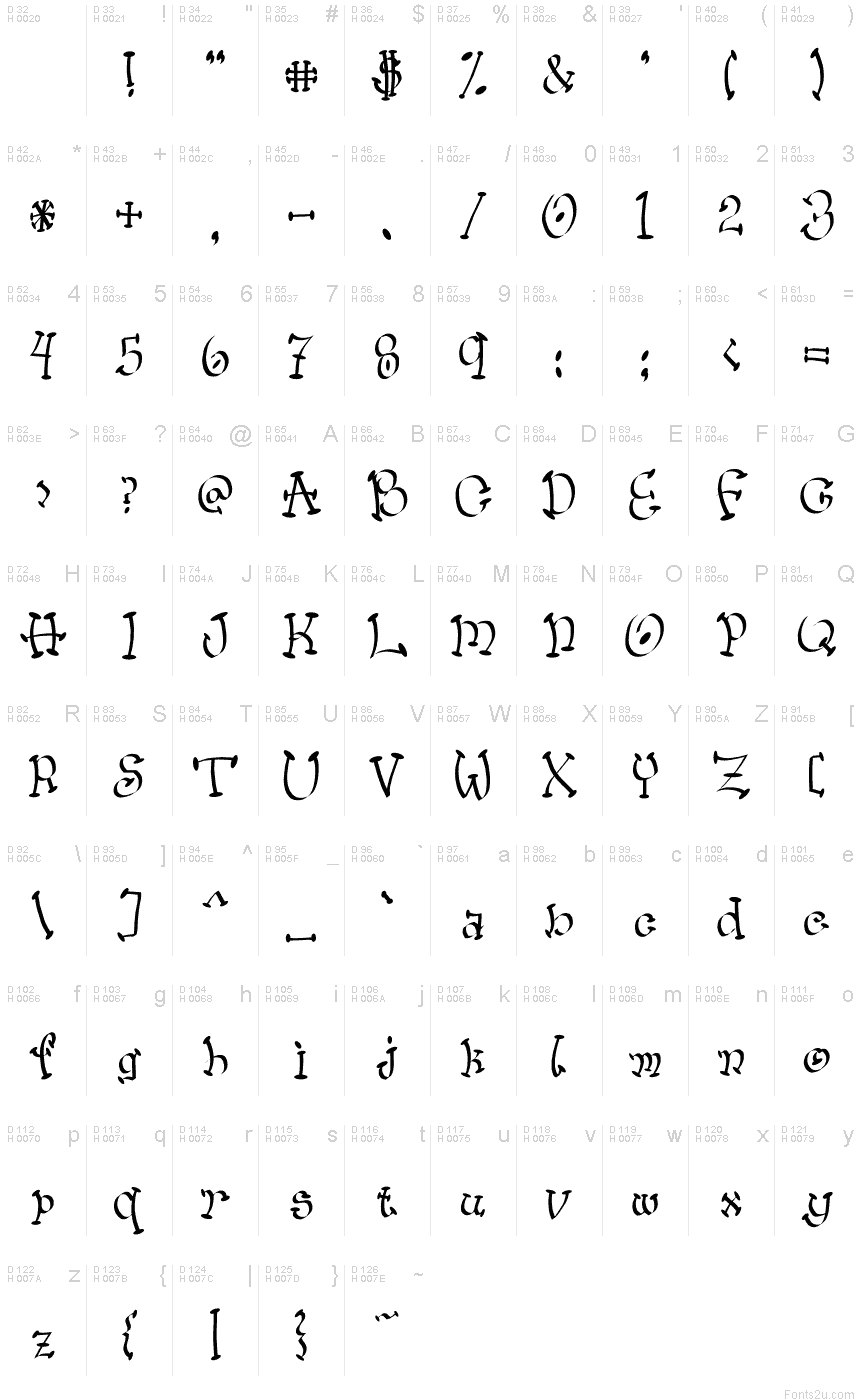
Wacko от A.J. Palmer — это бесплатный рукописный шрифт в стиле граффити с дерзким, мультяшным характером. Буквы наклоняются и «прыгают» благодаря толстым мазкам, коротким штрихам и гипертрофированным засечкам, что придает дизайну нервный, шумный и слегка хулиганский вид.
Он идеально подходит для случаев, когда нужно ощущение спонтанного леттеринга: обложки зинов, скейт-флаеры, наклейки музыкальных групп, афиши вечеринок и короткие заголовки — отличная среда для этого бесплатного шрифта. Используйте его, когда словам не хватает живости и озорства, а не «вылизанности», особенно в броских заголовках или монограммах, где эти пухлые и неровные формы говорят сами за себя.